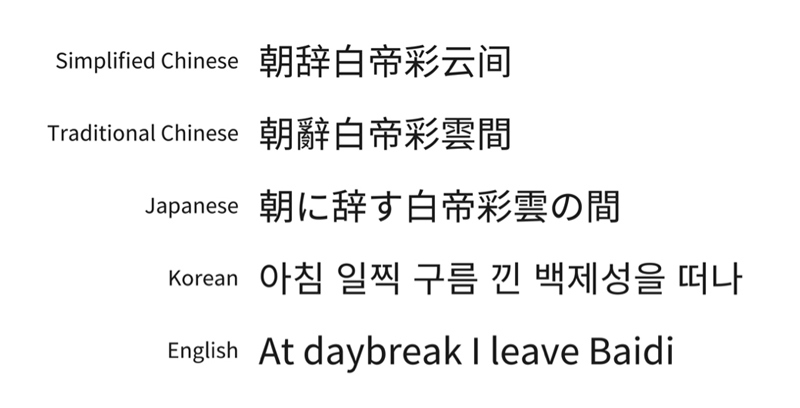
25 anni di font, uno speciale carattere gratuito da Adobe
Per celebrare i 25 anni nel mondo dei font, Adobe ha rilasciato un carattere gratuito, “Source Han Sans”, nuova famiglia di font open source che avvicina e armonizza in qualche modo il design di caratteri est asiatici e latini. Sviluppato nel corso di tre anni, è uno dei più complessi font che Adobe abbia mai progettato poiché per crearlo è stata indispensabile la collaborazione di cinque diverse società per disegnare centinaia di migliaia di glifi aiutati da esperti di composizione in lingua cinese, giapponese e coreana.
I caratteri asiatici sono utilizzati da circa un quarto della popolazione mondiale e le varianti OpenType prevedono alcune funzioni non disponibili in altri font PostScript e TrueType. I font OpenType asiatici offrono tipicamente glifi alternativi per molti caratteri e la possibilità di impostare metriche e glifi diversi per l’orientamento orizzontale e verticale, utili per rappresentare suoni contratti, doppie consonanti e indici fonetici.
Adobe si è occupata della gestione del progetto e del reclutamento delle expertise tecnologiche; Google e altri partner hanno collaborato al testing e con feedback. Il risultato è un font che si armonizza perfettamente con le famiglie Source Sans di Adobe e Noto Sans di Google e risolve il problema di mantenere una certa coerenza quando si indicano in un documento testi in lingue diverse come possono essere l’inglese e quelle asiatiche.
Source Han Sans prevede sette tipi di varianti da “Light” a “Heavy”, per un totale di 450,000 diversi glifi; nonostante questo, il font “pesa” la metà di altri caratteri CJK (termine che indica le tre principali lingue parlate nell’Asia Orientale: cinese, giapponese e coreano): meno di 19MB, anziché i 40 o più MB di altri, un parametro importante tenendo conto del possibile  font incorporato in documenti, siti o app per dispostivi mobili. È anche possibile ridurre ulteriormente il “peso” del font, scaricando la variante nella sola lingua di proprio interesse (circa 5MB per ognuna di queste).